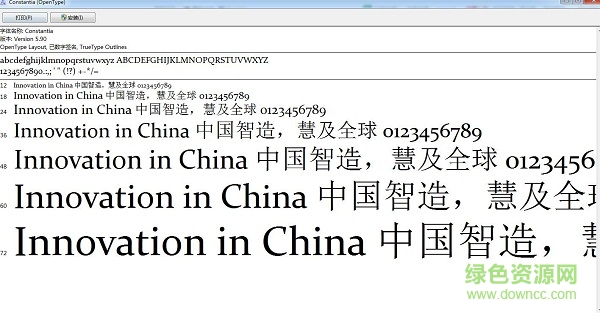
软件介绍 软件标签: constantia字体 衬线字体 constantia字体是一款衬线字体,包含了constantia 普通体和bold两种字型,有粗有细,挺劲秀美,可用于word排版方面,整体效果令人赏心悦目,欢迎大家免费下载!常用字体介绍【仿宋字体】仿宋为正方形,笔画均匀,起笔和落笔呈倾斜形,常用于古书封面和传统的包装设计及报刊标题。标准仿宋体字体 免费版授权:免费软件 WinAll, WinXP, Win7, Win8, Win10大小:2.4M语言:中文标准仿宋字体官方版是一款以gb2312编码表为标准的免费仿宋字体,清秀典雅,笔画粗细一致,清晰度高,这款字体适合用于正文排版之中,需要仿宋体的小伙伴快来下载吧!GB2312编码介绍GB2312编码适用于汉字处理、汉字通下载地址【细圆字体】比划圆顺舒展,结构秀逸婉转,字体匀称美观,适用于书、报、杂志的正文及装帧、广告等宣传用字。锐字云字库细圆体gbk 授权:免费软件 WinAll, WinXP, Win7大小:4KB语言:中文锐字云字库细圆体1.0gbk字体是一款纤细圆润的字体,字体线条锐利,结构沉着,使用效果不错,有兴趣的小伙伴欢迎在绿色资源网下载!字体安装方法方法一:控制面板/字体/文件/安装新字体;方法二:直接将字体复制到下载地址constantia字体安装说明方法一:控制面板/字体/文件/安装新字体;方法二:直接将字体复制到C:\WINDOWS\Fonts。 软件截图 上一张下一张(1 / 1) 安装详细截图 其他版本下载 标题 大小 更新日期 下载 下载地址 电脑版 constantia bold 点击报错 软件无法下载或下载后无法使用,请点击报错,谢谢! 关闭报错反馈 请描述您所遇到的错误,我们将尽快予以修正,谢谢! *必填项,请输入内容 本类最新 dreamweaver字体库 首尔南山体字体 v1.06 官方版 潮字社风云简ttf 潮字社凌渡鲲鹏简体字体 潮字社曾玉波手书简字体 微博慧心字体 相关文章 让你的XP/Vista也禁用U盘自动运行 上网安全三种禁用Cookie的方法 SATA硬盘安装XP的解决方法 .Net基础:ASP.NET中的session存储模式运用 通过PHP实现DataGrid功能 Vista系统下复制文件提速的妙招 用户评论 热门评论 最新评论 发表评论 查看所有评论(0) 昵称: 请不要评论无意义或脏话,我们所有评论会有人工审核. 字数: 0/500 (您的评论需要经过审核才能显示)